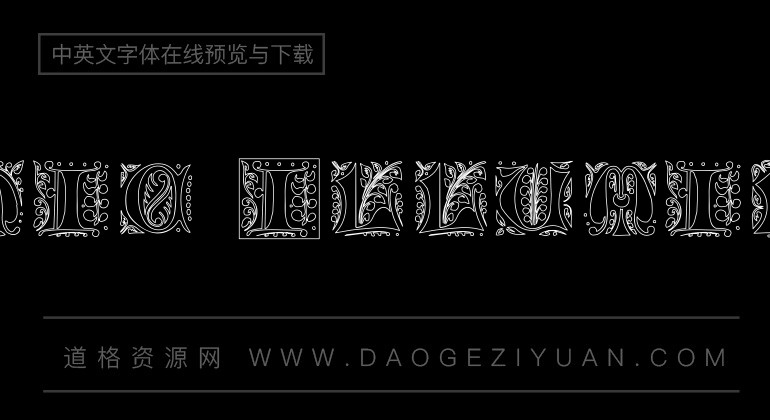
? Gothic Illuminate 字体是一款受到古典文艺复兴时期的启发而设计的现代字体。它的设计特点是细节丰富,笔画精致,笔画轻柔,字形优雅。它可以用于印刷,网页设计,标志,标题,广告,书籍封面,海报,卡片等等,是一款灵活性强的字体。内容介绍
Gothic Illuminate是一款非常不错的手写艺术字体,具有很好的视觉感,适合于文化类的宣传设计、商业类品牌的广告和产品包装设计以及个性化文字排版等较多场景。